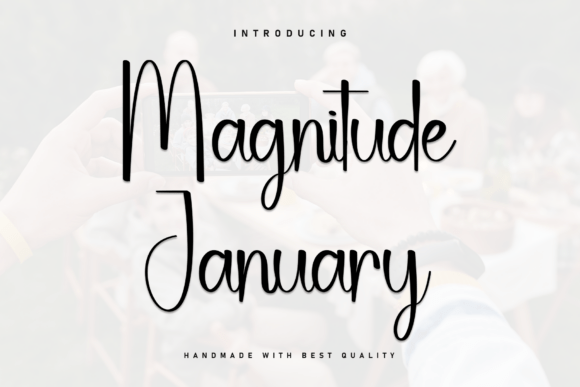
Magnitude January
Việc tìm kiếm các thành phần thiết kế phù hợp có thể là một thách thức, nhưng Magnitude January cung cấp một bộ sưu tập đặc biệt giúp nâng tầm công việc của bạn ngay lập tức.
Được chế tác với độ chính xác cao, Magnitude January cung cấp các vector sạch, kiểu chữ mượt mà và giấy phép thương mại để bạn yên tâm.
Cho dù bạn đang tạo sản phẩm POD (In theo yêu cầu), thiệp mời đám cưới hay đồ họa mạng xã hội, Magnitude January đều là một sự lựa chọn lý tưởng.